ペヤング 激辛やきそばEND
まるか食品からカップ焼きそば「ペヤング」の新商品としてペヤング史上最強の激辛であり、体中が熱く燃え上がる一品「激辛やきそばEND」が2018年8月27日に発売された。
ペヤング激辛やきそば、ペヤング史上最も辛かった「もっともっと激辛やきそば」を更に2倍辛くしたカップ焼きそば。
極限までの辛さを実現し、口の中が刺激され体が熱くなる程の辛さに仕上げました。
また、ENDの香辛料にはりんごピューレ、トマトペースト、ポークエキスなどを使用されている。
パッケージのフォントも恐怖を煽りまくる「ペヤング 激辛やきそばEND」を食べてみた。
「ペヤング 激辛やきそばEND」を購入。パッケージのフォントがゾンビ映画のようで、恐怖を煽りまくってくる。
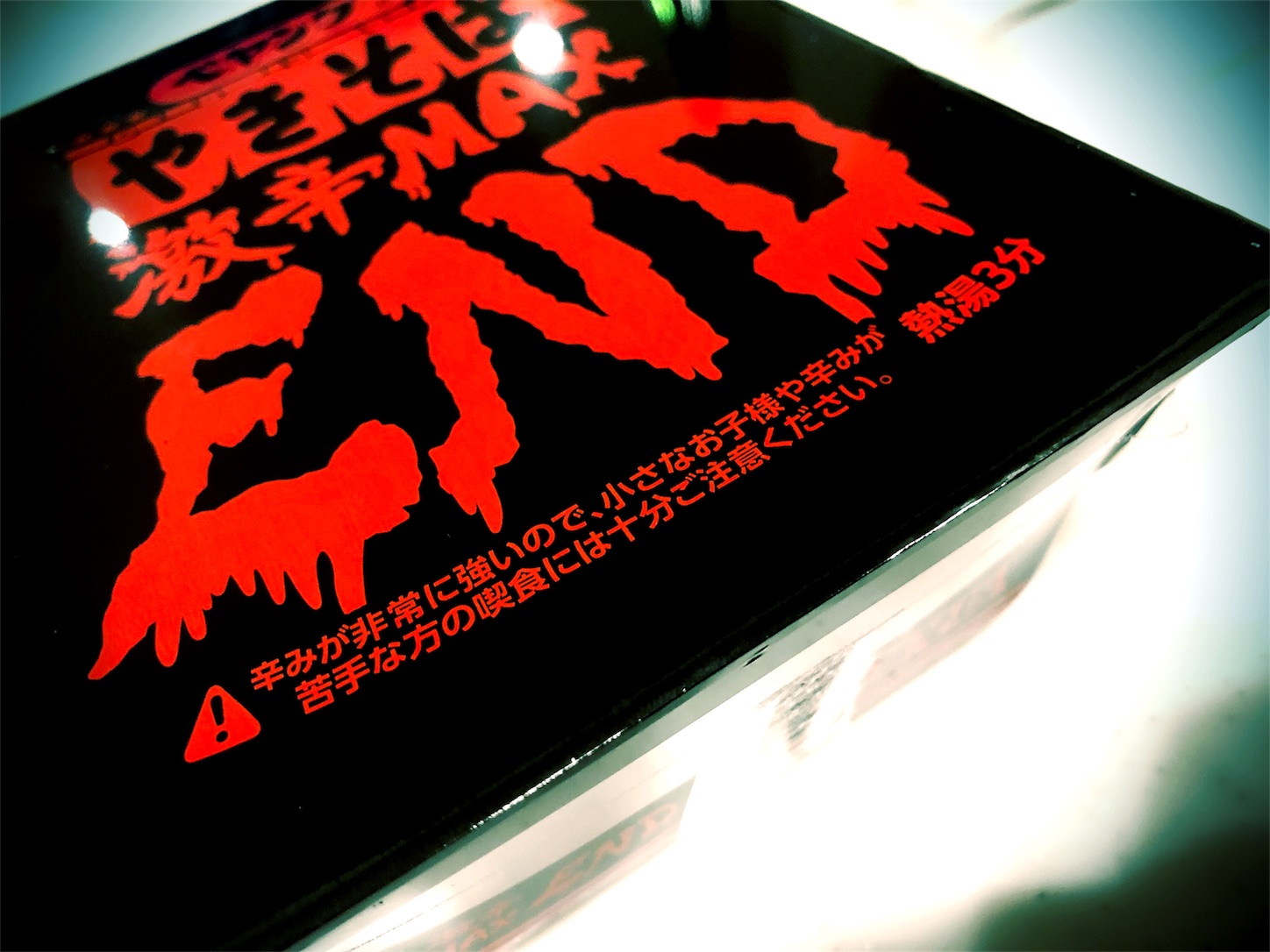
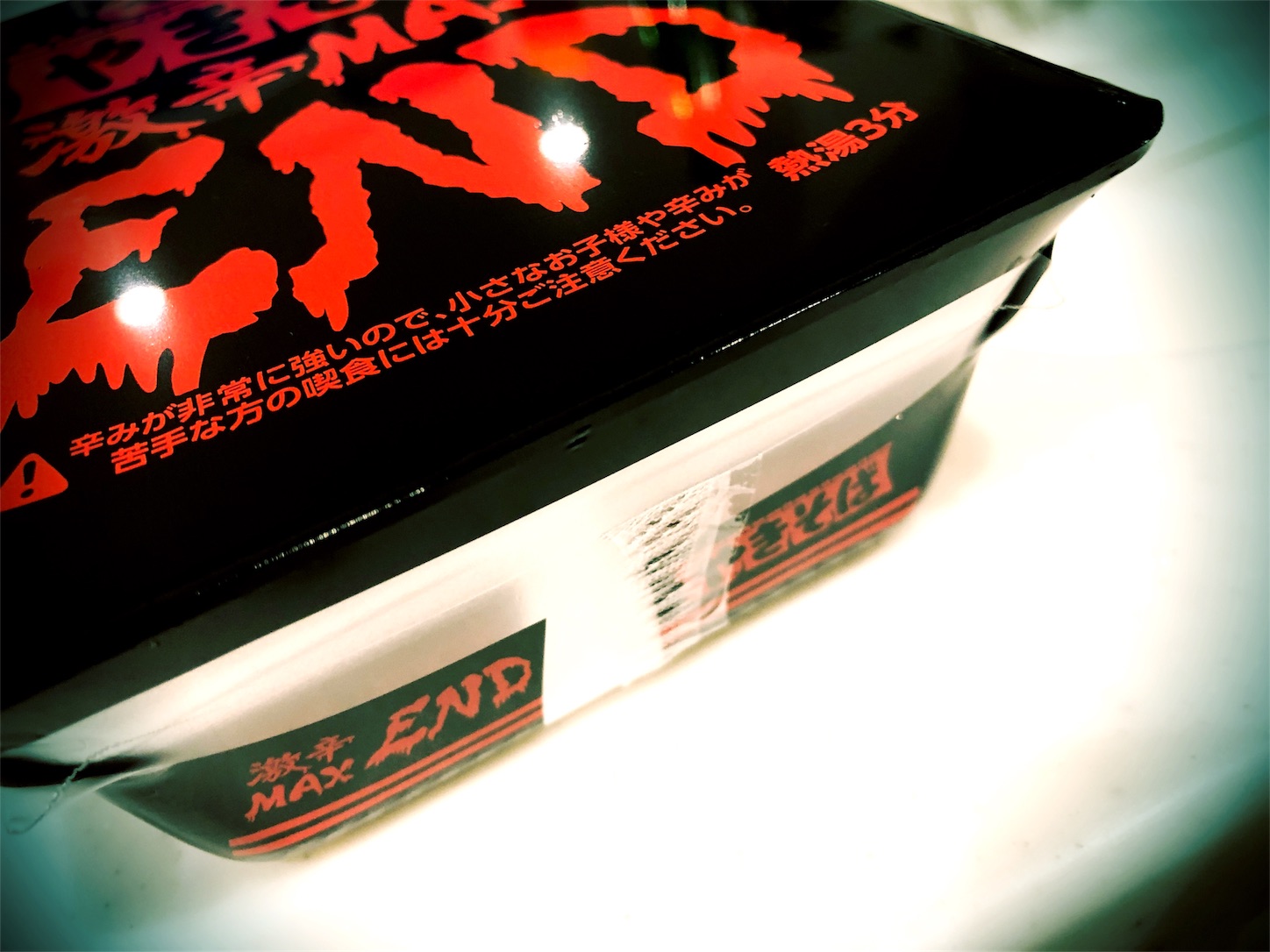
袋をやぶると中身は普通。
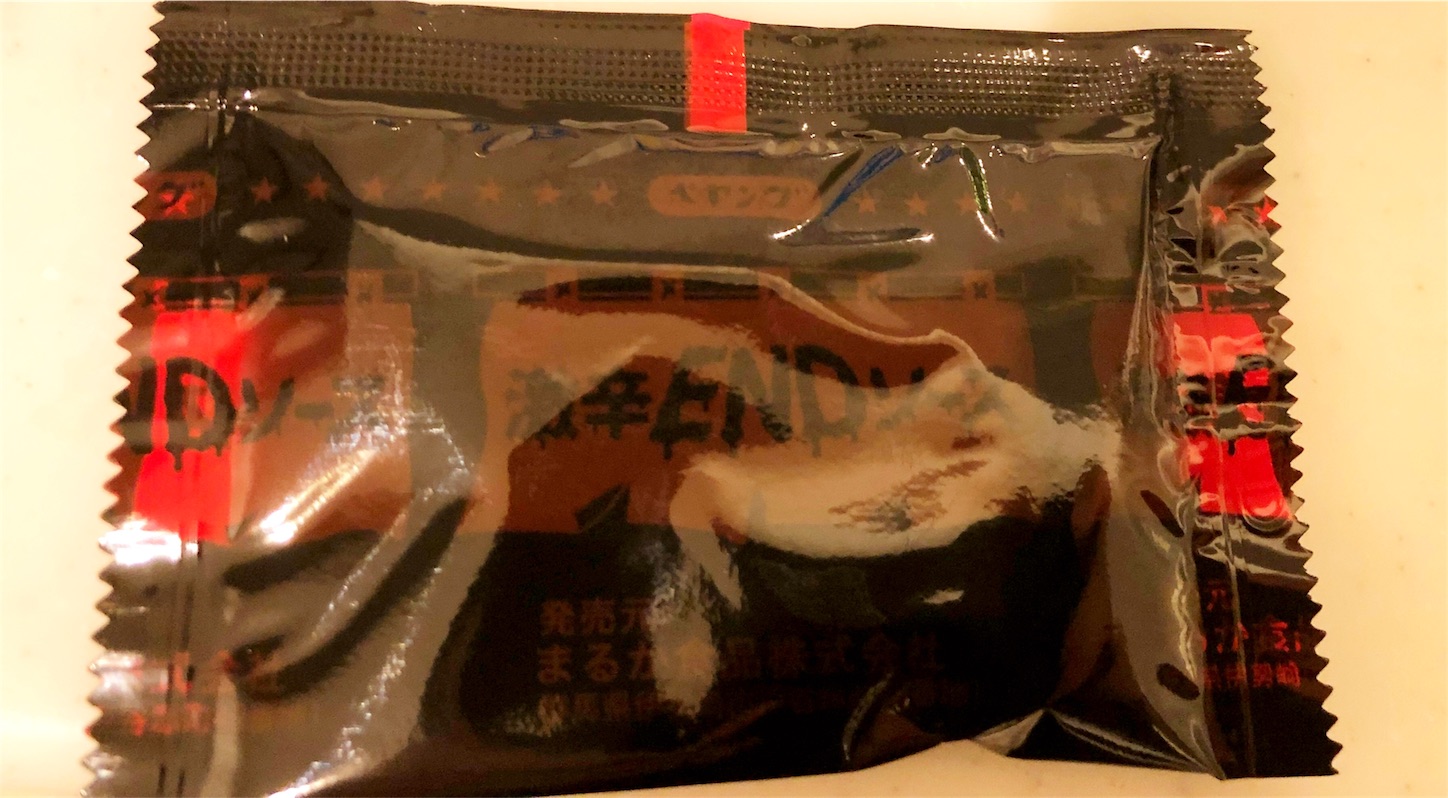
ソースの袋もパッケージ同様にホラー系。
ここも普通の白いペヤング。
ここまでは普通の白いペヤング。
はい、黒さが増しました。
辛そうで恐怖のあまり目玉焼きをトッピング。
スライスチーズも乗せる安全策で食す。
食事中、辛さで唇は痛くなったが普通に食べきれた。
食後、腹痛で便所で悶えた。